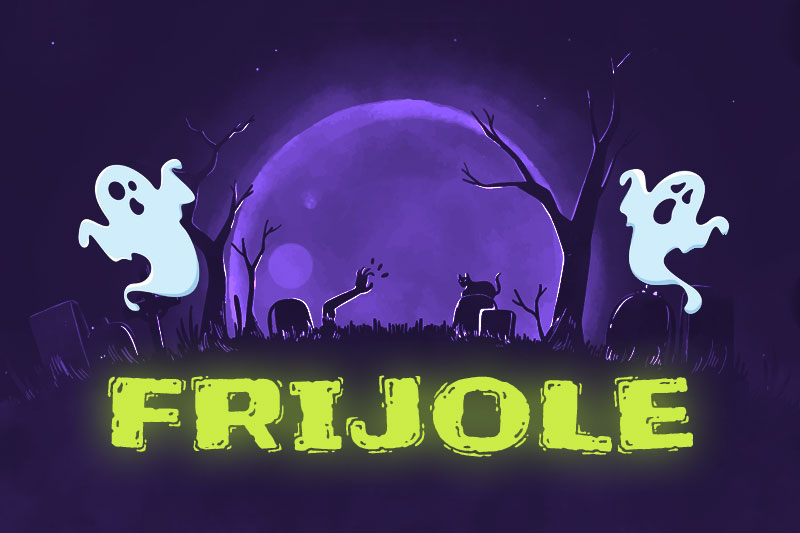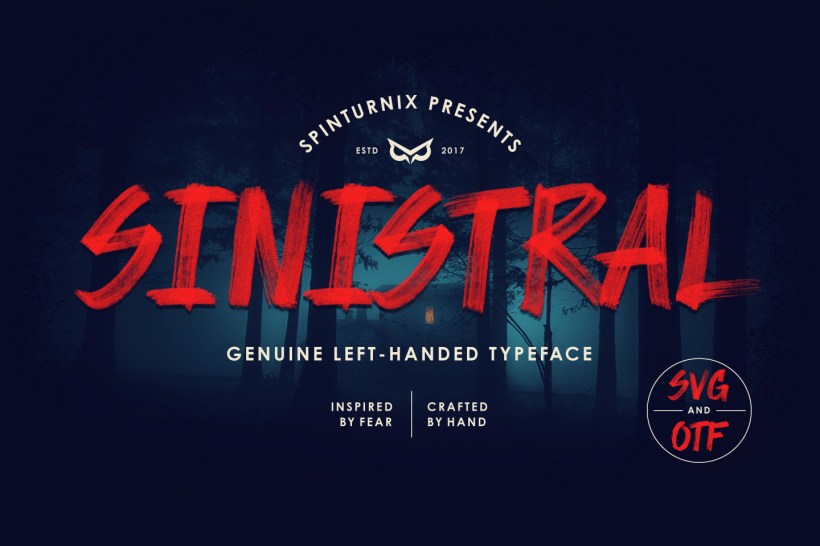
En ce mois d’octobre et à l’approche d’Halloween, vous aurez peut-être des designs avec une apparence effrayante sur lesquels travailler. Par exemple, des affiches, des dépliants, des bannières pour les réseaux sociaux ou des cartes d’invitation que vous allez devoir concevoir avec cette thématique.
Par ailleurs, vous avez certainement entendu à quel point il est important de choisir les polices appropriées pour ces créations visuelles… Aussi, j’ai sélectionné pour vous, dix polices d’écriture gratuites et parfaitement splendides pour tous vos design !
Certaines de ces typographies feront plutôt référence à l’horreur pur et simple, alors que d’autres relèveront du fantastiques. Dans tous les cas, ce sont des polices que vous pouvez utiliser pour vos créations d’Halloween.
Mystery Quest
Mystery Quest est une typographie avec de belles courbes qui rappelle bien l’esprit d’Halloween. Cette police d’écriture ludique peut être utilisée sur différents modèles et elle comprend des lettres majuscules et minuscules, des chiffres et une ponctuation de base.
Frijole
Frijole est une police d’écriture comportant seulement des lettres majuscules, des chiffres et une ponctuation de base avec un effet fantomatique. Une typographie au style effrayant et singulier a utiliser pour Halloween !
Sinistral
Sinistral est une typographie manuscrite inspirée des films d’horreur des années 80 avec une touche de modernisme.
Creepster
Creepster est une police d’écriture parfaite pour une large gamme de designs graphiques d’Halloween. Essayez cette typo gratuite pour une ambiance dégoulinante et effroyable !
Helloghost
Hello Ghost est une typographie incroyablement unique, effrayante et amusante collant créée spécialement pour la fête d’Halloween.
Hive
Chaque lettre de cette typographie gratuite prend la forme d’un monstre extravagant et parfaitement dans l’esprit d’Halloween.
Mexican Knappett
Pour une ambiance Día de Muertos, la fête des morts typique de la culture mexicaine, n’hésitez pas à utiliser la typographie gratuite Mexican Knappett !
Homicide Effect
HoMicIDE EFfeCt est typographie créée par Nihilschiz. Cette police d’horreur donnera un effet sanguilonant à tous vos design !
Griffy
Créee par Font Diner, Griffy peut apporter une touche effrayante à vos créations, n’hésitez pas jeter un œil !
The Gingerbread House
La typographie fantaisiste Gingerbread House créee par Chris Hansen est gratuite pour un usage personnel et comporte des lettres majuscules et minuscules.